创意美术字属于美术字体一类,是经由宋体、黑体、书法这些基本字体衍生而来的,它可以是黑体,可以是宋体,可以是书法体,也可以是其中两种或三种字体的结合变形。字体不单纯是一个设计上的范畴,因为它是我们人与人之间传递信息,相当于是一个视觉语言。创意美术字体就是设计师对作品最直观的艺术表达。我们一起来探索下面这些图片字体的魅力吧。
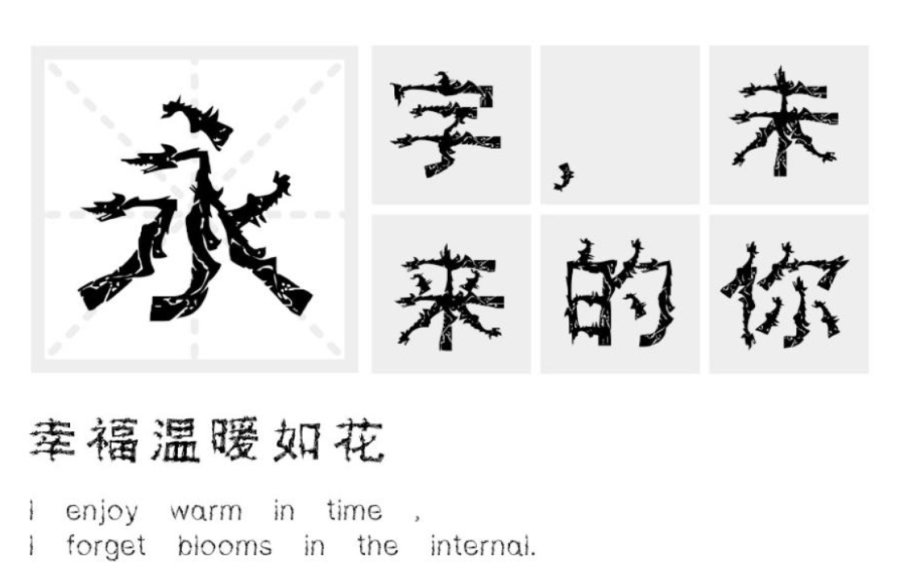
汉标华夏龙体:通常字形中的点、撇、捺、钩、提等笔画各具面目,这款字体笔画运用了龙图形元素来构建,把这些笔画做成了龙,概括为飘逸的龙型,并且使左右舒展的笔画尽量对称,最大限度地简化笔画龙造型。
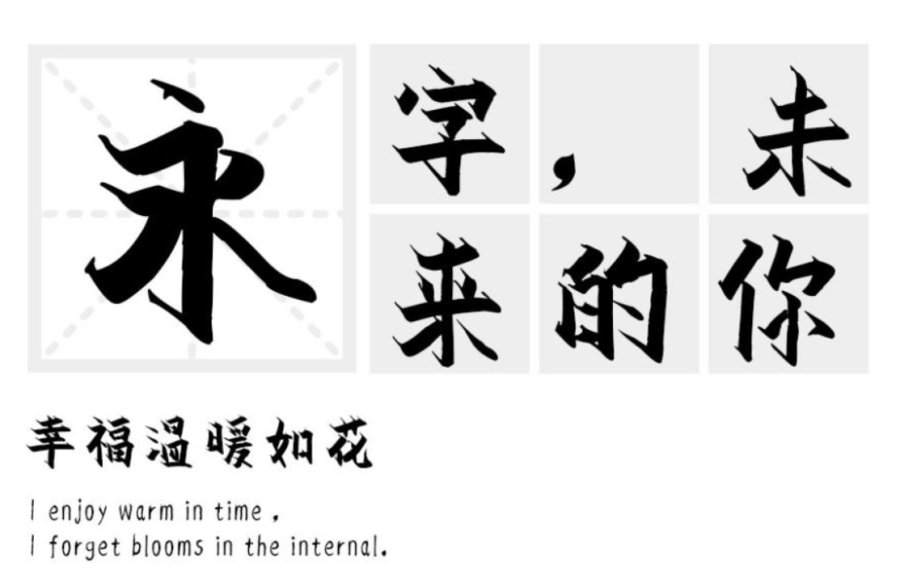
汉标雄安菲墨体:菲墨体是一款用软笔字,字型既有楷体的挺拔,又有硬笔独特的骨气。是一款非常实用的字体。因为字型灵活,书写感强,所以特别适合广告创意创作使用。
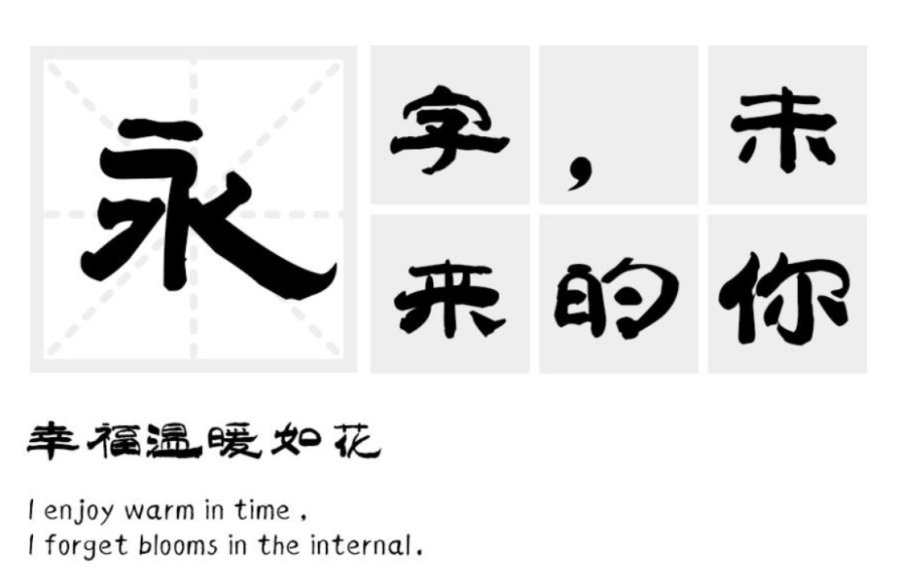
汉标太极体:作者在创作时力求太极元素,端庄平稳,中正安舒,易于字体识别、字型规范而不失特色。行书的运笔加入了一些抑扬顿挫及个别笔画的大舒展,形似人在打太极的感觉。